モテ字の法則 suiのペン字練習帳
「モテ字の法則 suiのペン字練習帳」は今までになかったペン字本となる。
「とにかく字が好み」「解説がわかりやすい」とTikTokで人気を集める穂さん(@sui1030)が、字に関する「あるあるな悩み」を解消。
きれいに見えるコツを徹底的に細かく解説して、万人からモテる字を目指してる。
もちろん、ひらがな・カタカナ・頻出漢字など、各種文字の書き方の基礎も学べる。
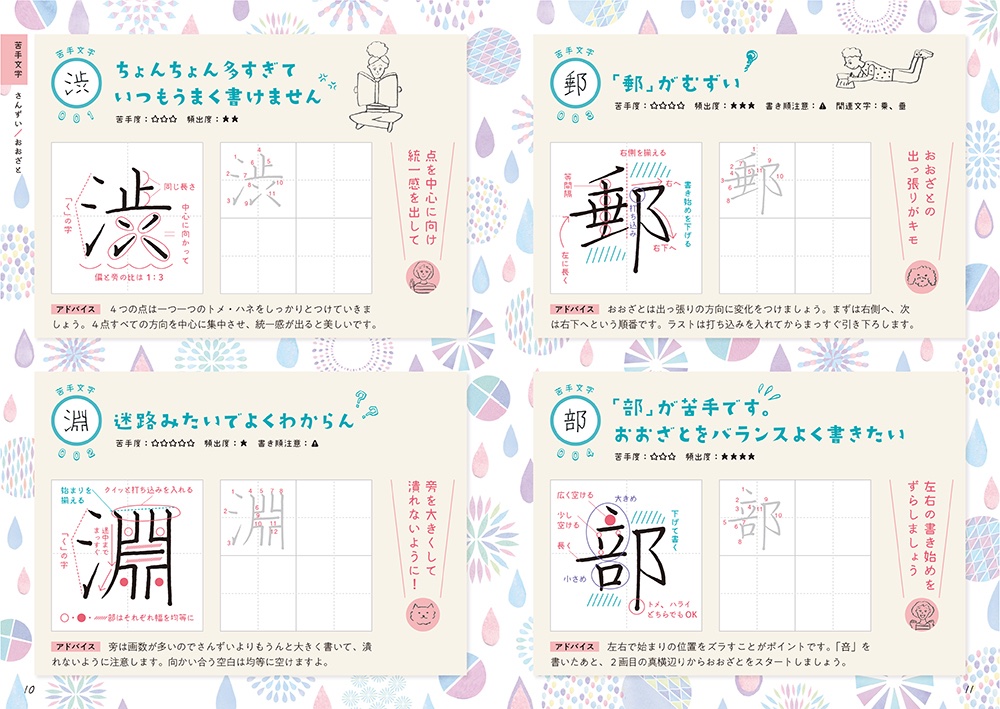
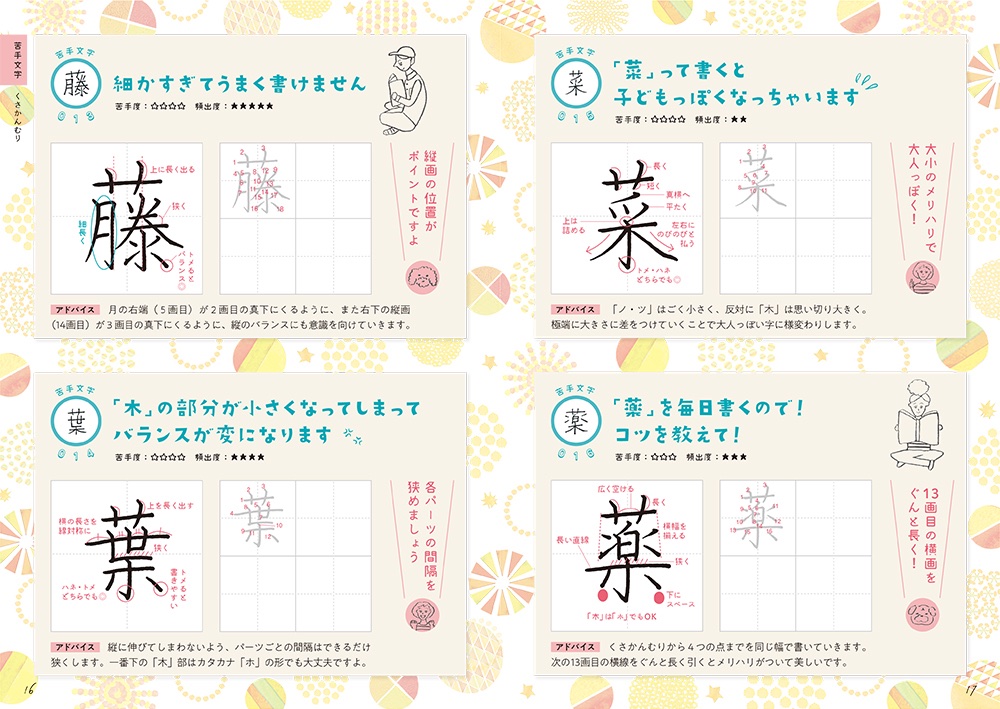
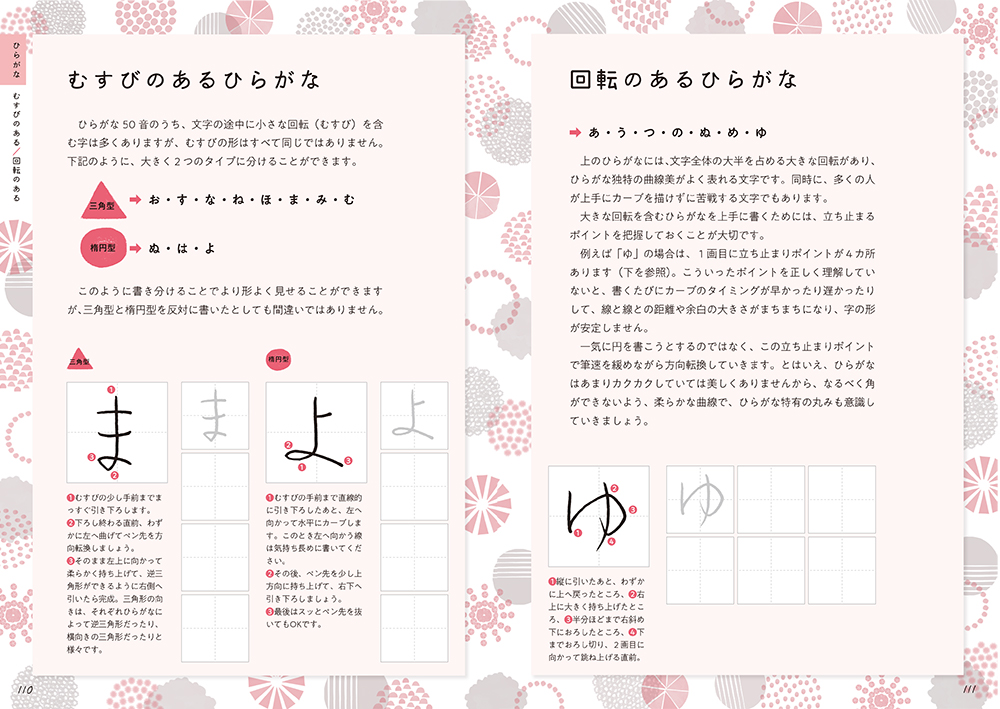
「モテ字の法則 suiのペン字練習帳」の特長
こんな字の悩みがある方は必読!「モテ字の法則 suiのペン字練習帳」
渋→ちょんちょん多すぎていつもうまく書けません
窓→窓がおじいちゃんの顔になる
園→園っていう字の中が口の中に収まらないです
卵→卵って書けば書くほど何が正解かわからなくなる
女→女とか、女がつく字が苦手です
妻→妻って書くとなんか虫みたいになっちゃいます
必→この漢字きれいに書ける人尊敬に値する
貝→下のハがむずい
為→いつもヘナチョコな字になる
ゆ→一番むずい
ん→「ん」が「人」に見えてしょうがない(;_;)
ク→「ワーク」が「ワーワ」になっちゃう
「モテ字の法則 suiのペン字練習帳」の内容
■part1 みんなの苦手文字200
■part2 ひらがなとカタカナ
■part3 部首とパーツ
■part4 特徴ある形の漢字
■part5 もっと! モテ字メソッド